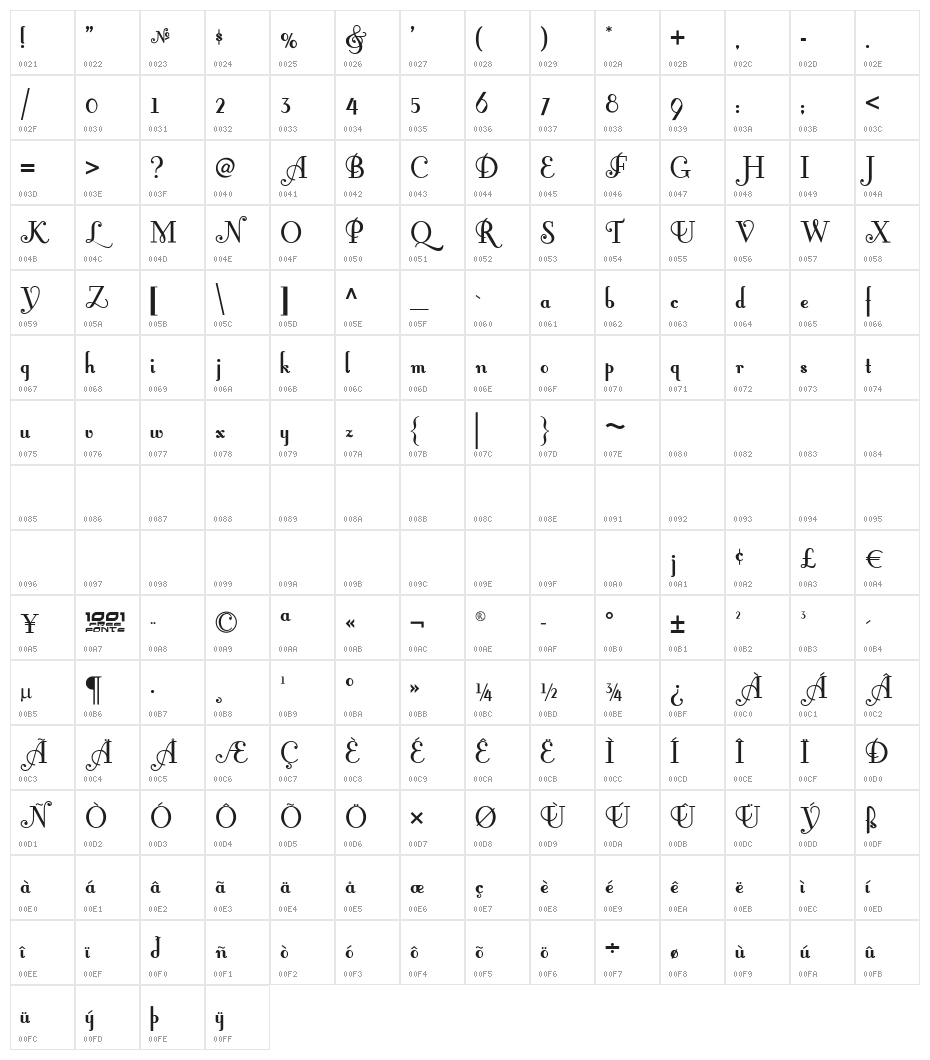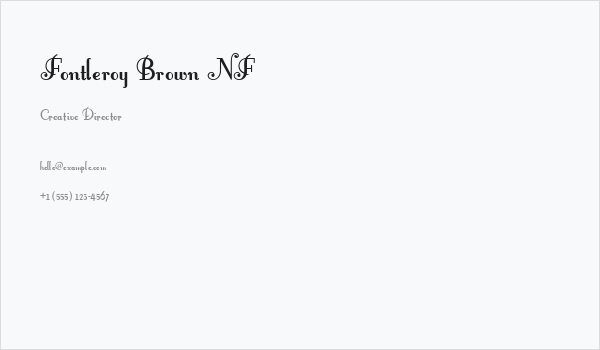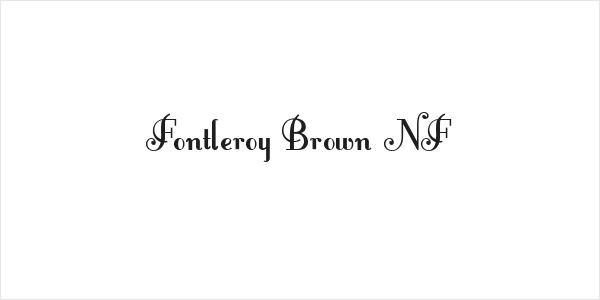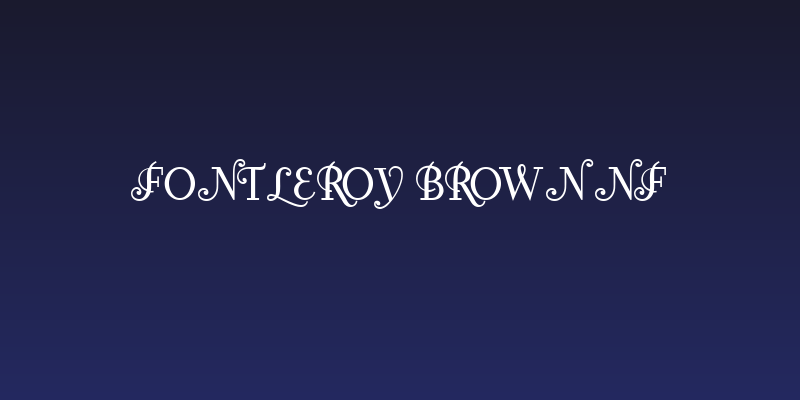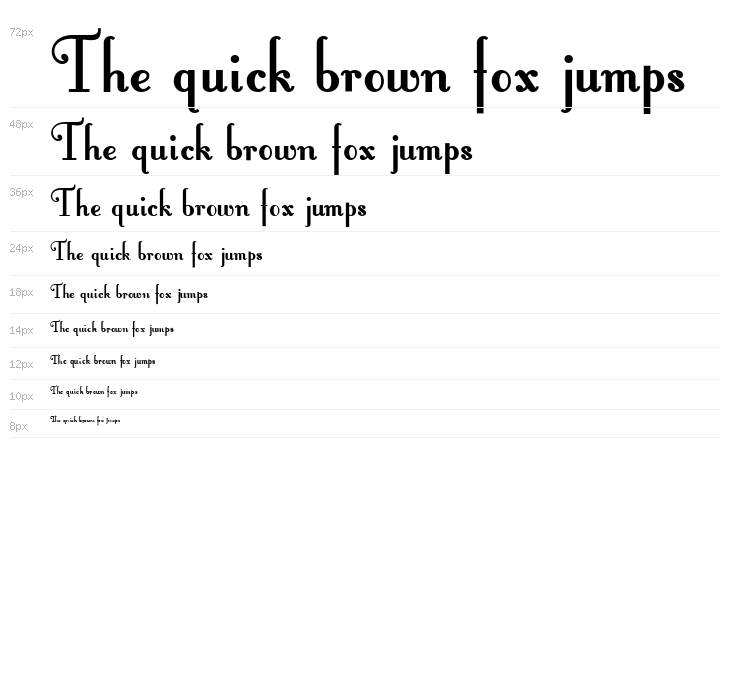
Fontleroy Brown NF Font
| Gesamtstil | Classic, Decorative |
| Anwendungsfall | Headlines, Logos, Invitations |
| Vorgeschlagene Projekte | Ideal for wedding invitations, luxury branding, decorative signage, and artistic projects. |